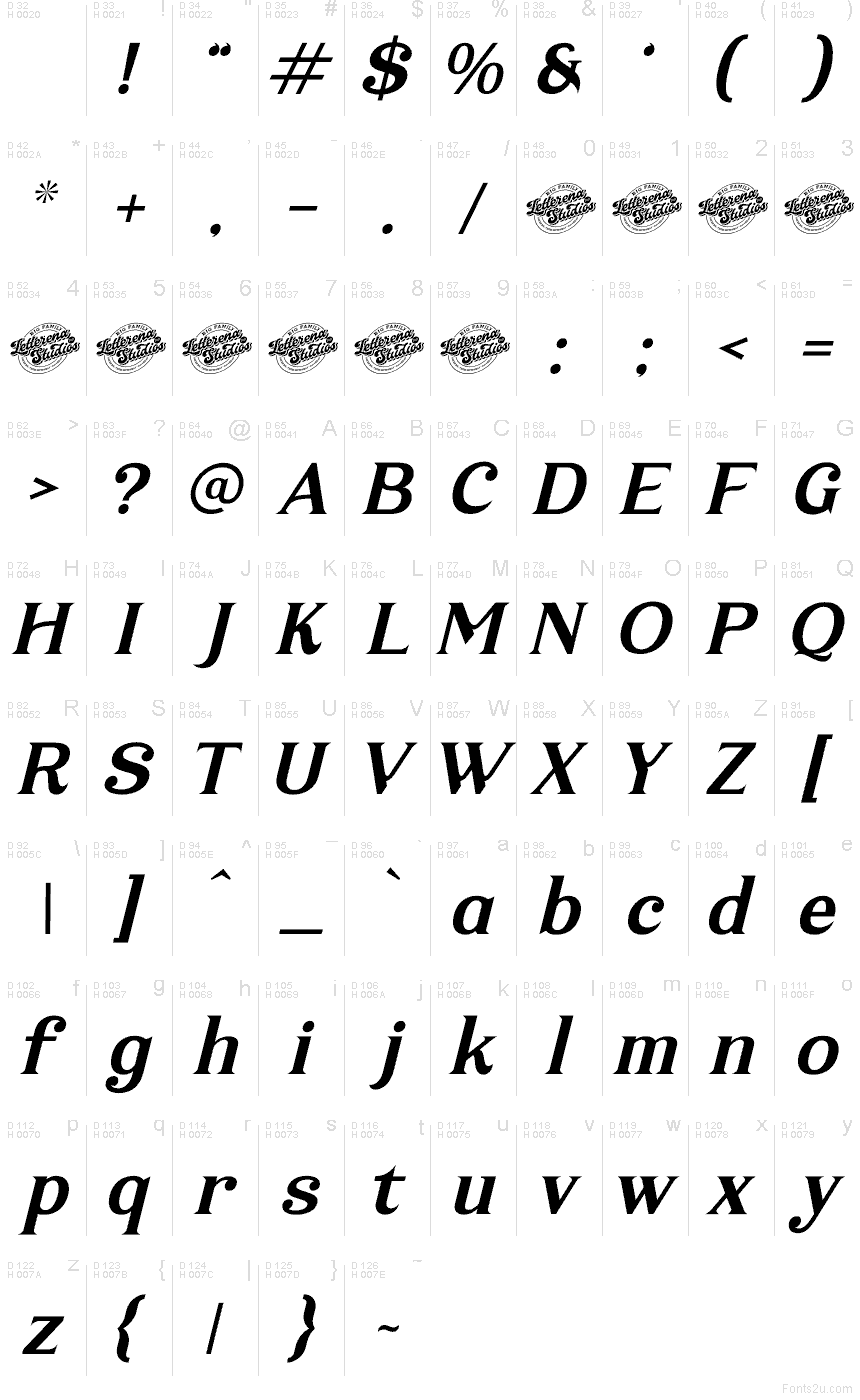
Mystic Grace DEMO VERSION Italic
Mystic Grace di Letterena Studios è un font calligrafico con grazie (serif) in corsivo, gratuito, caratterizzato da un tono romantico e ispirato al mondo della moda. Le lettere combinano curve ampie con grazie affilate e sottili, dando vita a un carattere che punta innanzitutto sulla grazia, senza risultare eccessivamente formale, grazie a un ritmo fluido che lo rende vibrante anziché rigido.
Si adatta perfettamente a branding, packaging di prodotti di bellezza, insegne di boutique, copertine di riviste e inviti, dove un tocco di eleganza è essenziale per definire l'atmosfera. Essendo un font gratuito, è ideale anche per titoli, citazioni e intestazioni brevi, specialmente quando cerchi quell'eleganza ad alto contrasto senza scadere nell'eccesso decorativo.